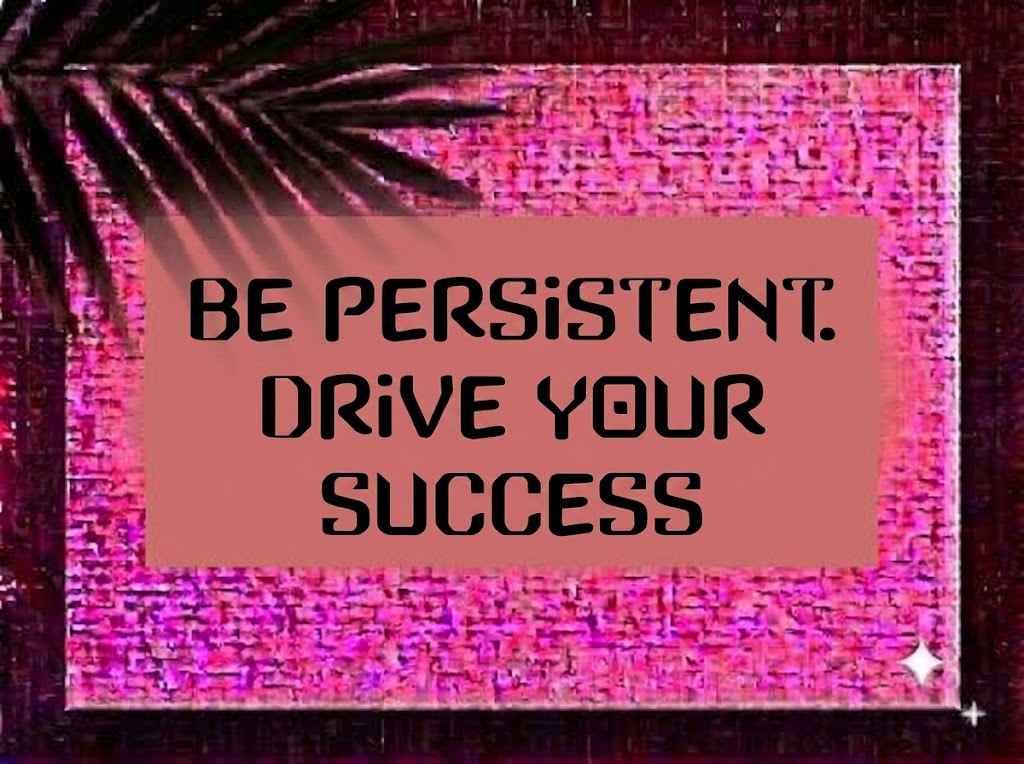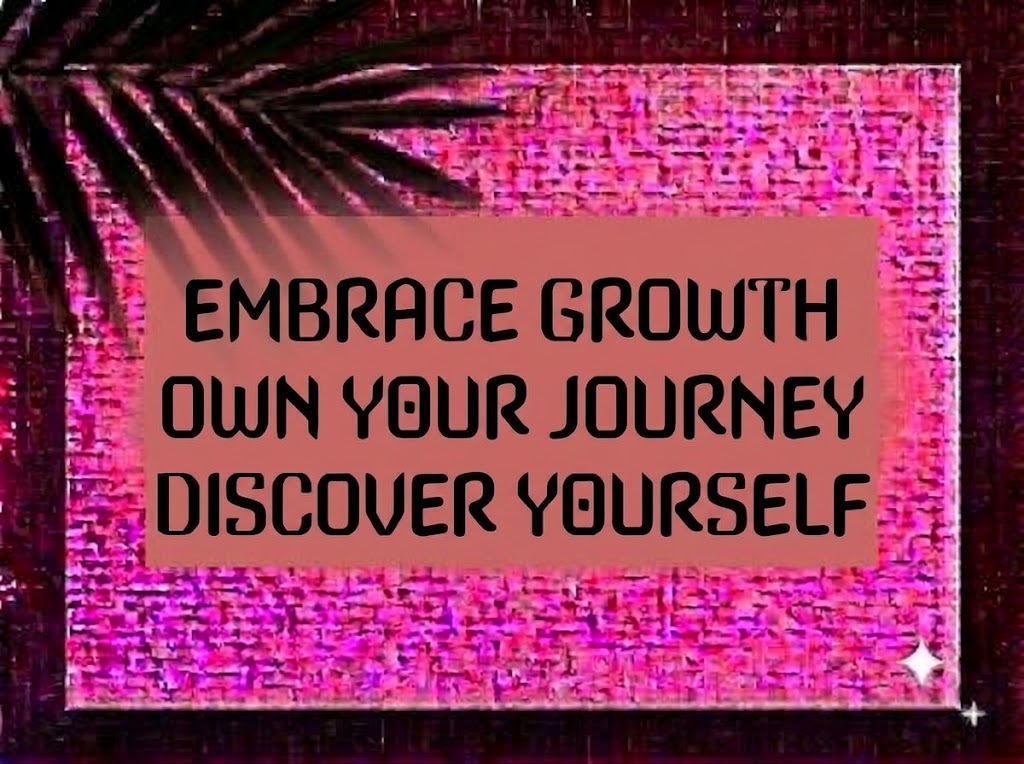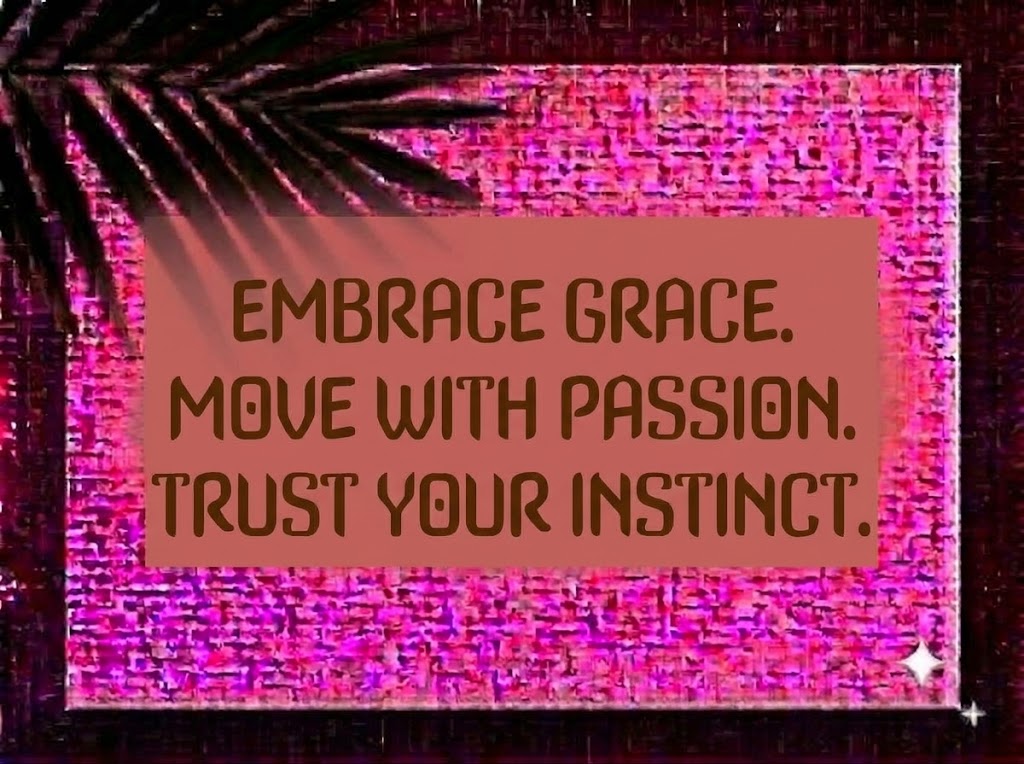
1FTV VIP Avixariav
Trong nghệ thuật thiết kế đồ họa thị giác và truyền thông giải trí đương đại, phong cách typography mang âm hưởng thần thoại cổ đại (Mythology), ký tự cổ (Runic) kết hợp cùng hình khối cơ học viễn tưởng (Sci-Fi Fantasy) luôn sở hữu sức hút huyền bí và khác biệt.
Nếu bạn đang tìm kiếm một phông chữ hiển thị độc lạ, mang đậm tinh thần thần thoại, nhập vai (RPG) để làm logo game, poster phim kỳ ảo, bìa sách hay tiêu đề video ngắn bùng nổ, font 1FTV VIP Avixariav chính là sự lựa chọn không thể bỏ qua.
Giới thiệu về font 1FTV VIP Avixariav
Font 1FTV VIP Avixariav là bộ chữ hiển thị trang trí (display font) phát triển theo trường phái Geometric Tribal & Ancient Fantasy, nổi bật với cấu trúc khối vuông kiên cố cùng các đường lượn hoa văn kỳ bí:
Đặc điểm nổi bật của phong cách thiết kế VIP Avixariav
Sức hút thị giác của font 1FTV VIP Avixariav đến từ sự giao thoa giữa cấu trúc hình học vuông vức và các đường cắt nét mang tính phù hiệu cổ xưa:
Khung chữ khối hộp kiên cố (Boxy Framework): Các con chữ được sắp đặt vừa vặn trong một khối hình chữ nhật đứng, tạo cảm giác bề thế, vững chãi tựa như những khối đá cự thạch khắc chữ cổ.
Dãy chữ số tạo hình mê cung độc đáo: Hệ thống số từ 0-9 được thiết kế với các đường gấp khúc lồng ghép tinh xảo, biến các con số ngày tháng hay cấp độ thành một tác phẩm nghệ thuật đồ họa riêng biệt.
Sự đồng bộ giữa các ký tự hoa và thường: Hệ thống chữ cái in hoa và in thường kết hợp liền mạch, giữ vững nhịp điệu thị giác uy nghi trên toàn bộ dòng tiêu đề.
Khoảng cách ký tự (Kerning): Khoảng hở giữa các khối chữ vuông được tính toán cân bằng, đảm bảo các chi tiết móc nhọn khi đứng sát nhau không bị va chạm hay gây cảm giác dính rối.
Hệ thống ký tự đồng bộ: Tích hợp trọn vẹn bộ chữ cái, dãy số 0-9 cùng đầy đủ các ký hiệu toán học và dấu câu cơ bản.
Hình ảnh demo thực tế của font 1FTV VIP Avixariav
Khả năng hiển thị của phông chữ được tối ưu linh hoạt theo nhiều kích cỡ:
Kích thước nhỏ (12pt – 24pt): Cấu trúc khối rõ ràng giúp các đoạn text ngắn và dãy số vẫn hiển thị rành mạch trên màn hình điện thoại di động.
Kích thước lớn (36pt – 72pt): Đây là đất diễn lý tưởng nhất để 1FTV VIP Avixariav phô diễn toàn bộ nét chạm khắc thần thoại, sự sắc lạnh và vẻ đẹp kỳ ảo cho các dòng headline chính.
Ứng dụng trong thiết kế đồ họa và làm video
Sở hữu nét cá tính huyền bí và đậm chất viễn tưởng, font 1FTV VIP Avixariav mở ra không gian ứng dụng phong phú:
Tựa game & Thể thao điện tử (Gaming & eSports): Lựa chọn hàng đầu để thiết kế logo tựa game thể loại nhập vai (RPG), MOBA, chiến thuật cổ đại, game thẻ bài ma thuật hoặc banner giải đấu game.
Video ngắn (TikTok, Reels, Shorts): Dáng chữ cổ điển độc lạ hiển thị rất bắt mắt trên khung hình đứng tỷ lệ 9:16. Cực kỳ ăn nhập với các clip gaming highlight, review phim kỳ ảo/khoa học viễn tưởng, video thần thoại hoặc âm nhạc Epic/Trailer music.
Ảnh thu nhỏ YouTube (Thumbnail): Lựa chọn hoàn hảo để giật tít cho các kênh phân tích cốt truyện game, giải mã truyền thuyết lịch sử, khảo cổ học hay thế giới huyền bí.
Poster Sự kiện, Phim ảnh & Thời trang Streetwear: Rất thích hợp làm poster phim điện ảnh giả tưởng, bìa album nhạc Rock/Metal, nhãn hiệu thời trang Darkwear, Techwear và in ấn áo thun graphic cá tính.